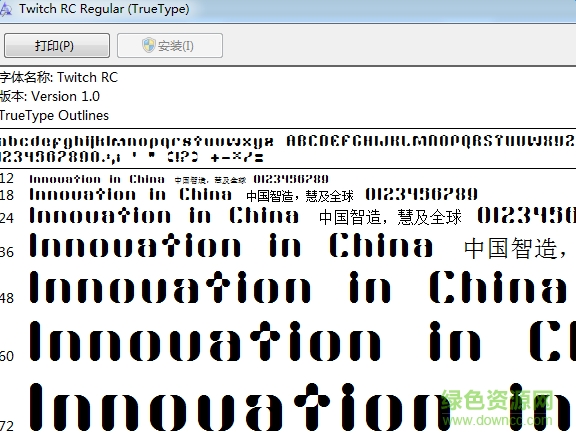
Twitch RC英文字體
Twitch RC字體是一款超好用的個(gè)性英文字體,該字體可以廣泛應(yīng)用于廣告設(shè)計(jì)、宣傳海報(bào)、ppt、影視制作以及任何使用文字的領(lǐng)域,有需要的朋友可以免費(fèi)下載收藏。
Twitch RC字體是一款極具個(gè)性的字體,該字體十分飄逸,彰顯了自己的個(gè)性,有喜歡的朋友可以來(lái)綠色資源網(wǎng)下載使用!